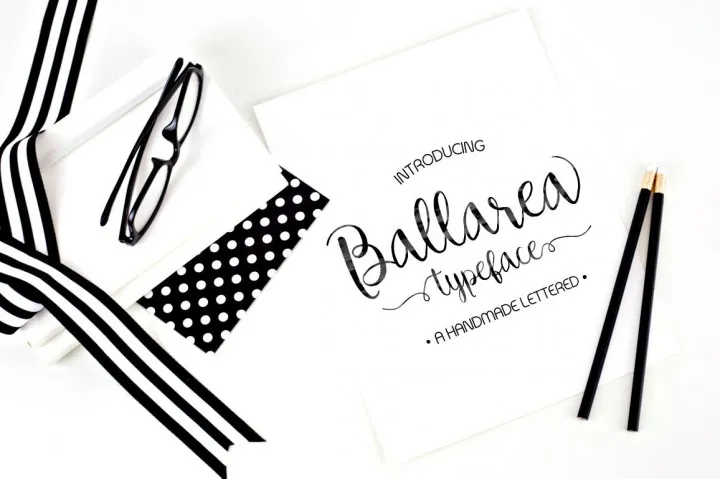
A Ballarea Font é uma preciosidade do universo das fuentes para escrita, oferecida gratuitamente pela Thehungryjpeg neste catálogo especializado em Calligraphy Fonts. Esta beleza vem do designer Hamilton, uma criação única que agora está disponível à disposição de todos gratuitamente por um período limitado, apenas 14 dias. Os amantes da arte e dos designers podem encontrar aqui uma fonte perfeita para trazer destaque a qualquer projeto de escrita artística ou tipográfica. A Thehungryjpeg mantém-se fiel às suas práticas de compartilhar gratuitamente recursos únicos, garantindo que cada utilizador possa explorar e apreciar esta maravilha da design gráfico enquanto ainda está disponível. Se deseja adquirir a essência desta fonte, é agora ou nunca – não perca este precioso momento para fazer parte deste catálogo de excelentes fuentes.